Miễn phí – Top font việt hóa Miễn phí tháng 2/2025
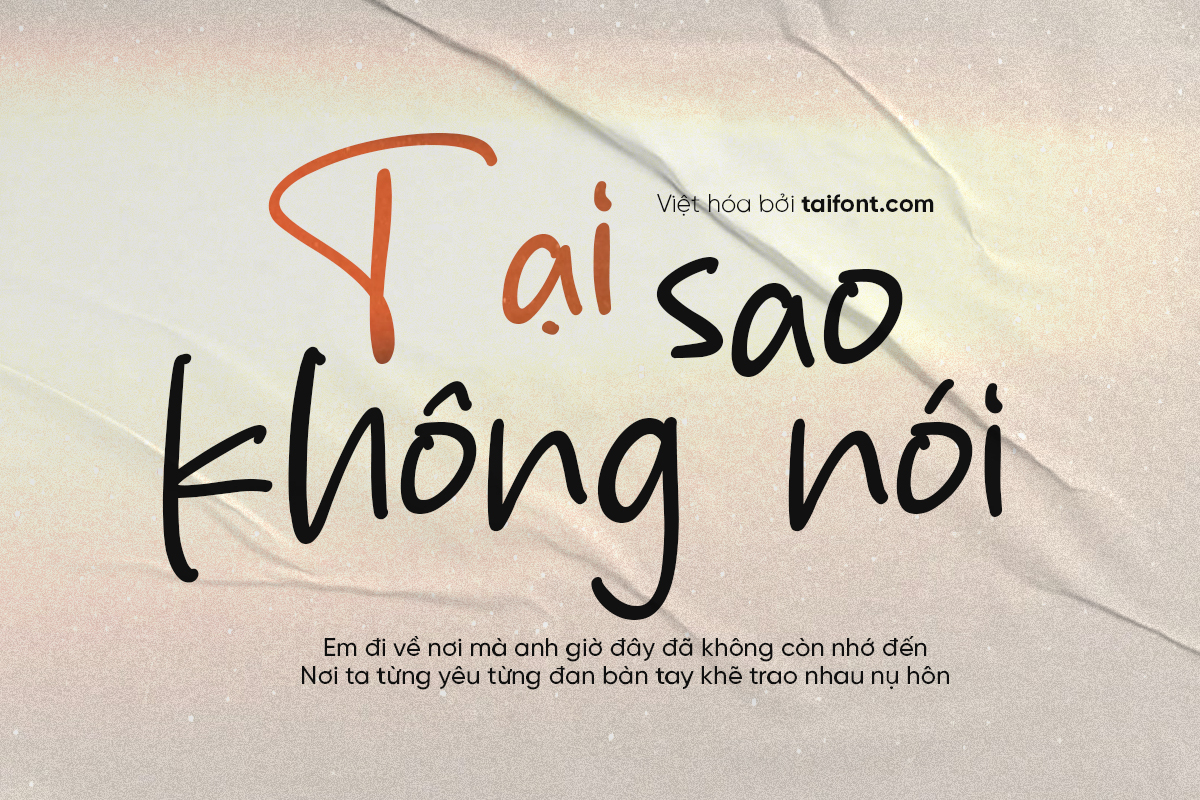
Miễn phí – Top font việt hóa Miễn phí tháng 2/2025, đây là những font Việt hóa miễn phí được cập nhật gần đây.
Font Việt hóa TF Simple Michael | Link tải
Font Việt hóa TF Simple Michael là font có chân, nét dễ thương phù hợp cho các thiết kế thời trang.
Font Việt hóa TF VIP Avigea | Link tải
Font Việt hóa TF VIP Avigea là một font chữ có chân có nét đậm, mập mạp. Font phù hợp với thiết kế tiêu đề cần sự rõ ràng để hiển thị thông tin.
Font Việt hóa TF Monster of Fantasy | Link tải
Font Việt hóa TF Hursy | Link tải
Font Việt hóa TF Hursy là một font chữ không chân đẹp, nét cứng rắng mạn mẽ phù hợp cho các thiết kế tiêu đề thể hiện rõ nét thông tin.
Font Việt hóa TF Fish Catcher | Link tải
Font Việt hóa TF Fish Catcher là một font chữ viết tay đã được Việt hóa cho người Việt sử dụng.